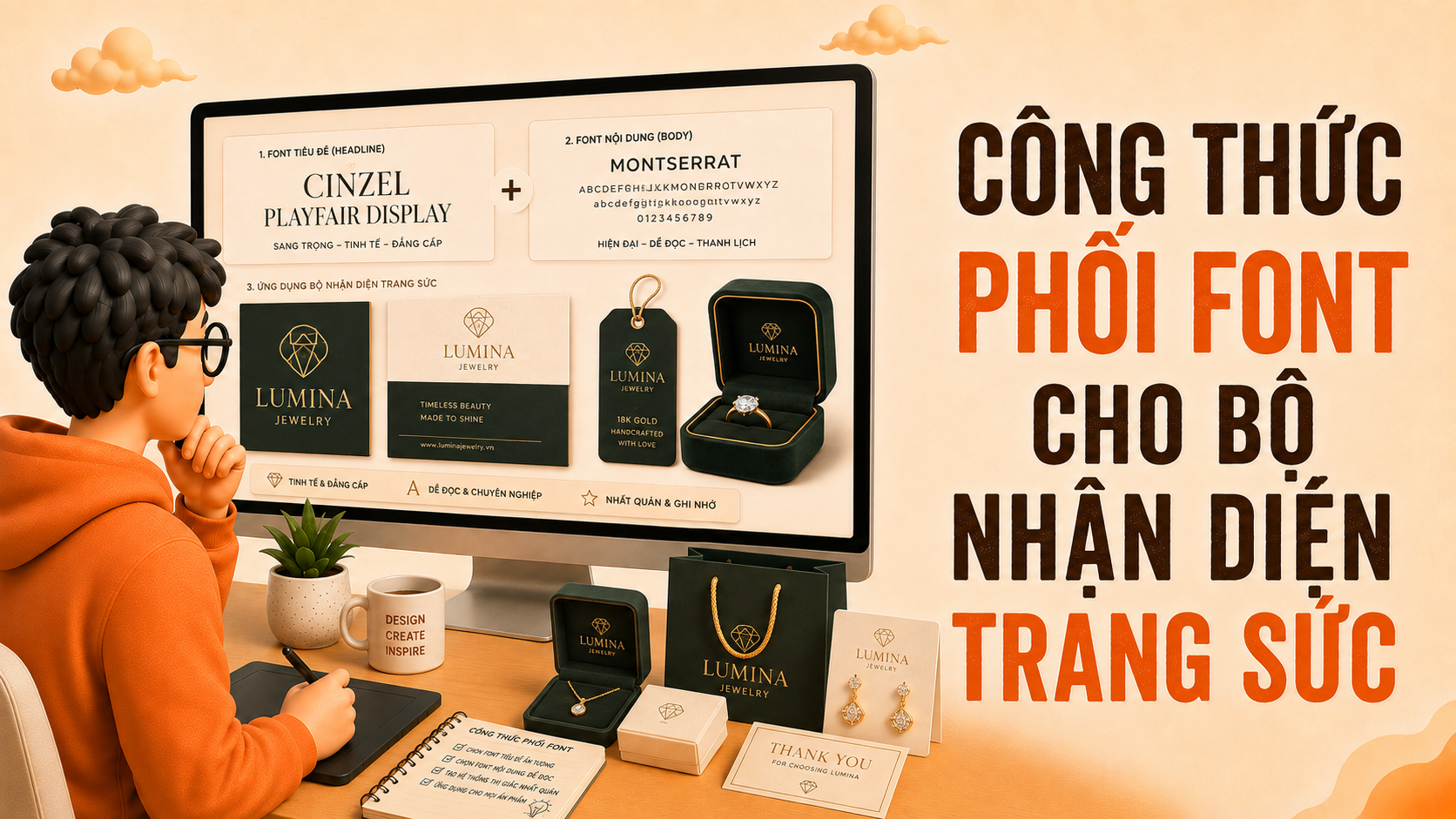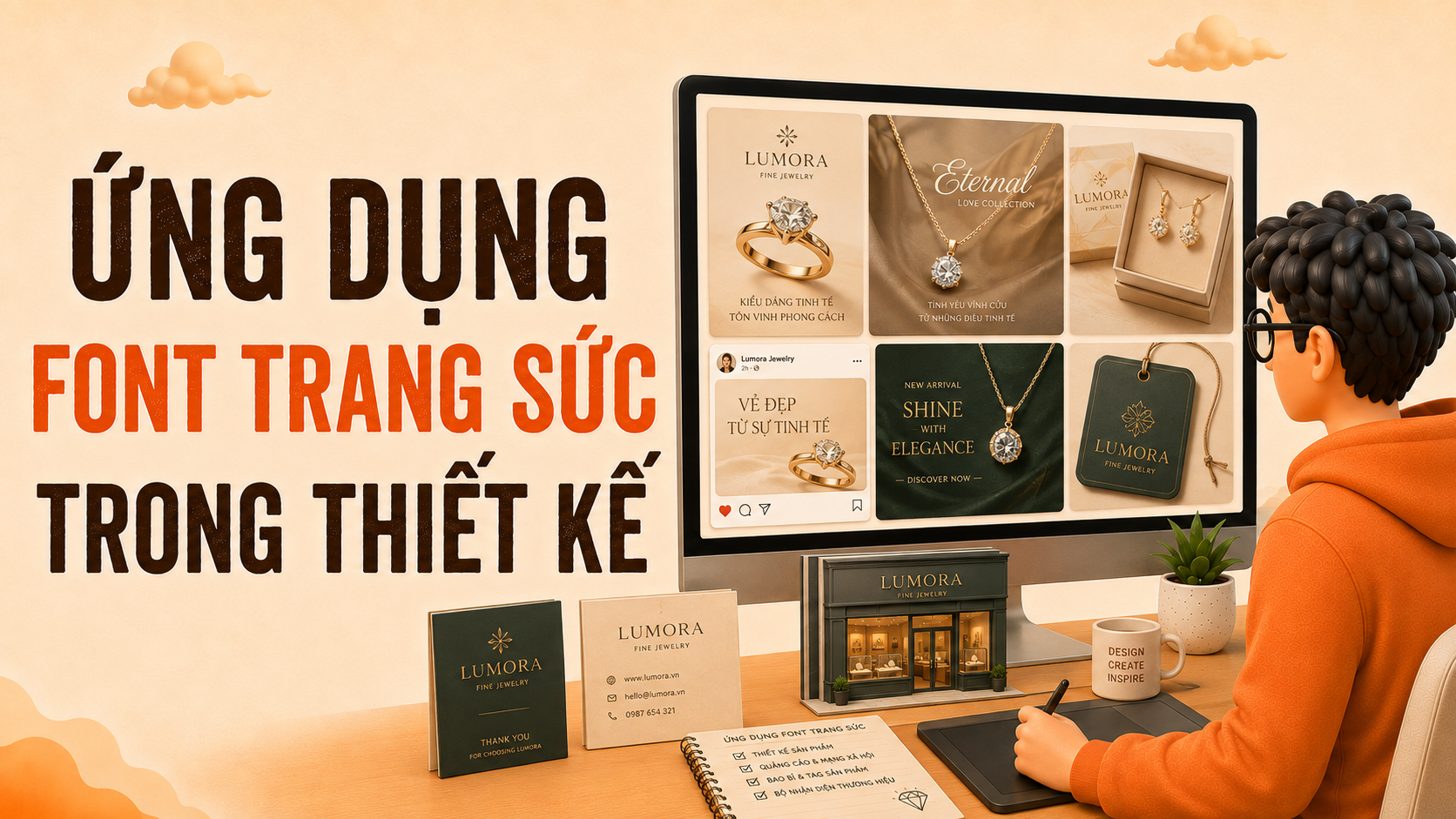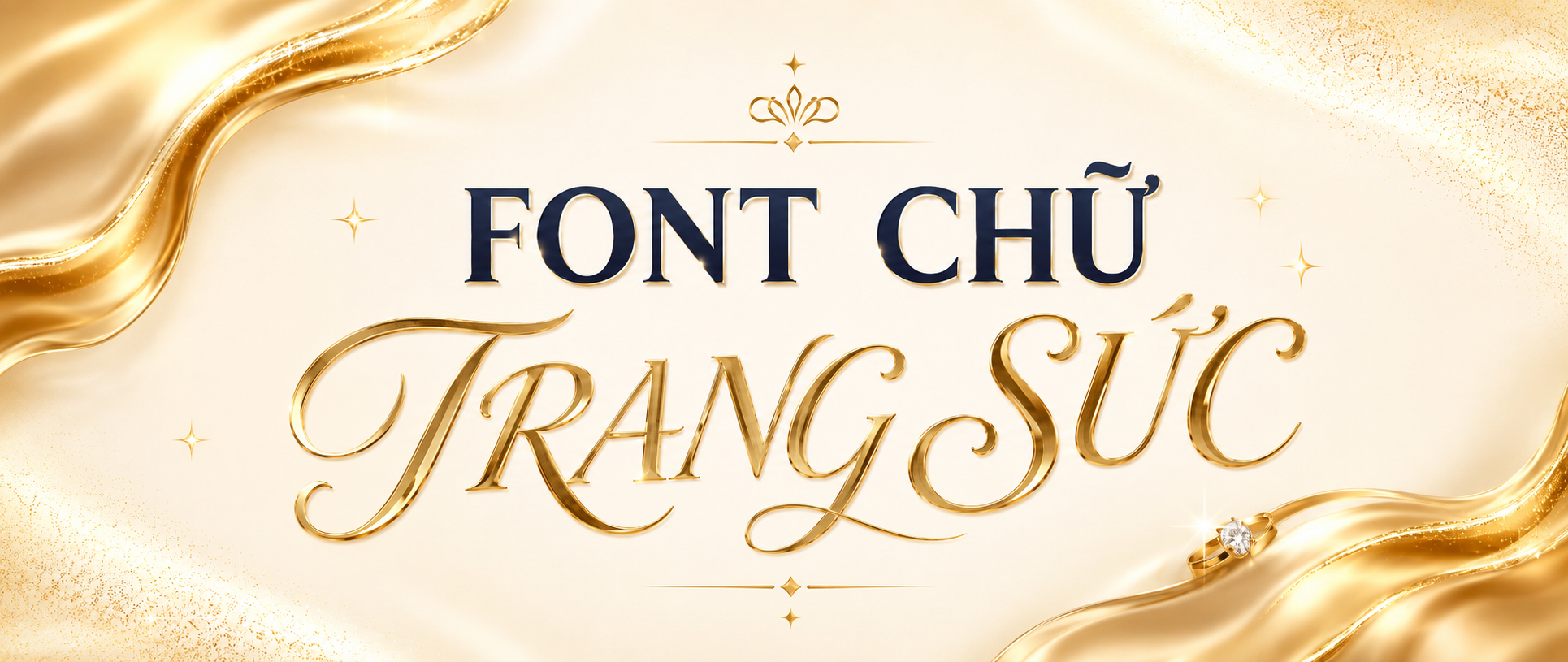
Trang sức là ngành mà chữ rất dễ làm thay đổi cảm giác giá trị. Cùng một chiếc nhẫn, một bộ vòng cổ hoặc một bộ sưu tập bạc, nếu dùng font sai, thiết kế có thể trở nên rẻ, nặng hoặc thiếu tinh tế. Vì vậy, font chữ trang sức cần vừa sang, vừa rõ, vừa giữ được cảm giác tin cậy khi xuất hiện trên logo, hộp đựng, tem nhãn, lookbook, banner sale và social.
Bài viết này gợi ý các font Việt hóa phù hợp trên Font S99 cho nhiều kiểu thương hiệu trang sức: tiệm vàng truyền thống, jewelry cao cấp, bạc tối giản, nhẫn cưới, đá quý, phụ kiện handmade và local brand trẻ. Mỗi font được trình bày thành một dòng riêng với anchor Tải về để bạn dễ chọn và thử trực tiếp trên thiết kế.
Thiết kế trang sức thường có ít chữ nhưng mỗi chữ đều quan trọng. Logo trên hộp nhẫn, tên bộ sưu tập trên lookbook, tagline trên poster, giá ưu đãi trên banner, tên đá quý trên catalogue hay dòng cam kết trên thẻ bảo hành đều góp phần tạo cảm giác cao cấp.
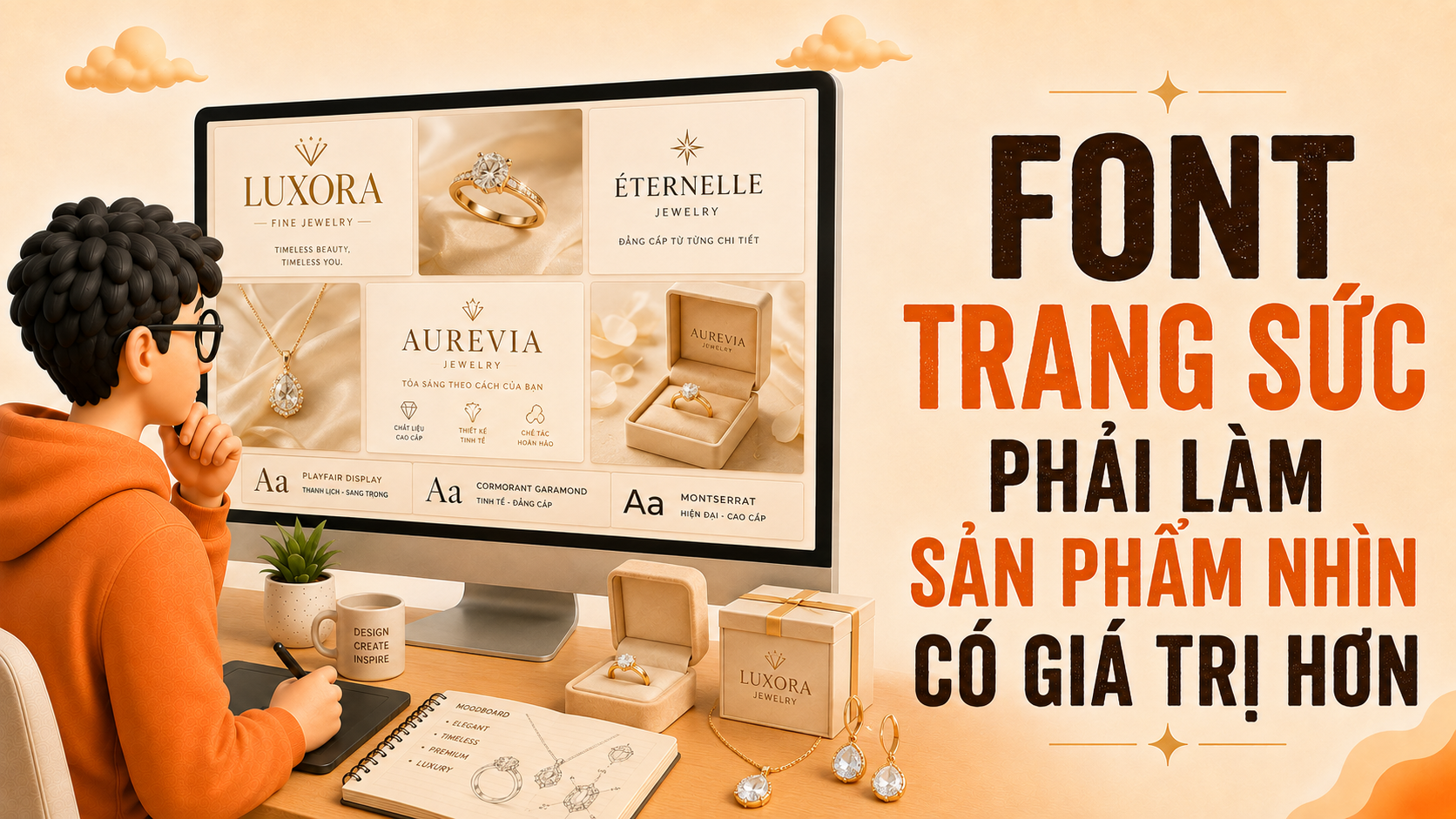
Một font tốt cho trang sức không nhất thiết phải quá cầu kỳ. Nó cần có tỷ lệ đẹp, nét chữ tinh, khoảng cách chữ thoáng và dấu tiếng Việt cân. Với ngành này, sự tiết chế thường sang hơn hiệu ứng. Chỉ cần một font serif thanh lịch hoặc một sans-serif gọn, đặt đúng khoảng trắng, thiết kế đã có thể đắt giá hơn nhiều.
Điểm cần tránh là dùng font quá dày, quá vui hoặc quá nhiều hiệu ứng kim tuyến. Trang sức vốn đã có độ lấp lánh từ ảnh sản phẩm. Font nên nâng sản phẩm lên, không tranh spotlight với sản phẩm.
Logo trang sức nên có cá tính rõ nhưng không khó đọc. Với thương hiệu vàng, đá quý, nhẫn cưới hoặc jewelry cao cấp, serif và luxury sans-serif là lựa chọn an toàn. Với bạc tối giản hoặc local brand trẻ, sans-serif mảnh, sạch và hiện đại sẽ hợp hơn.
Hộp trang sức thường có diện tích nhỏ. Font cần đọc rõ ở kích thước nhỏ, không bị mất nét khi ép kim, in bạc, in vàng hoặc in trên nền tối. Hãy thử logo ở nhiều kích thước trước khi chốt.
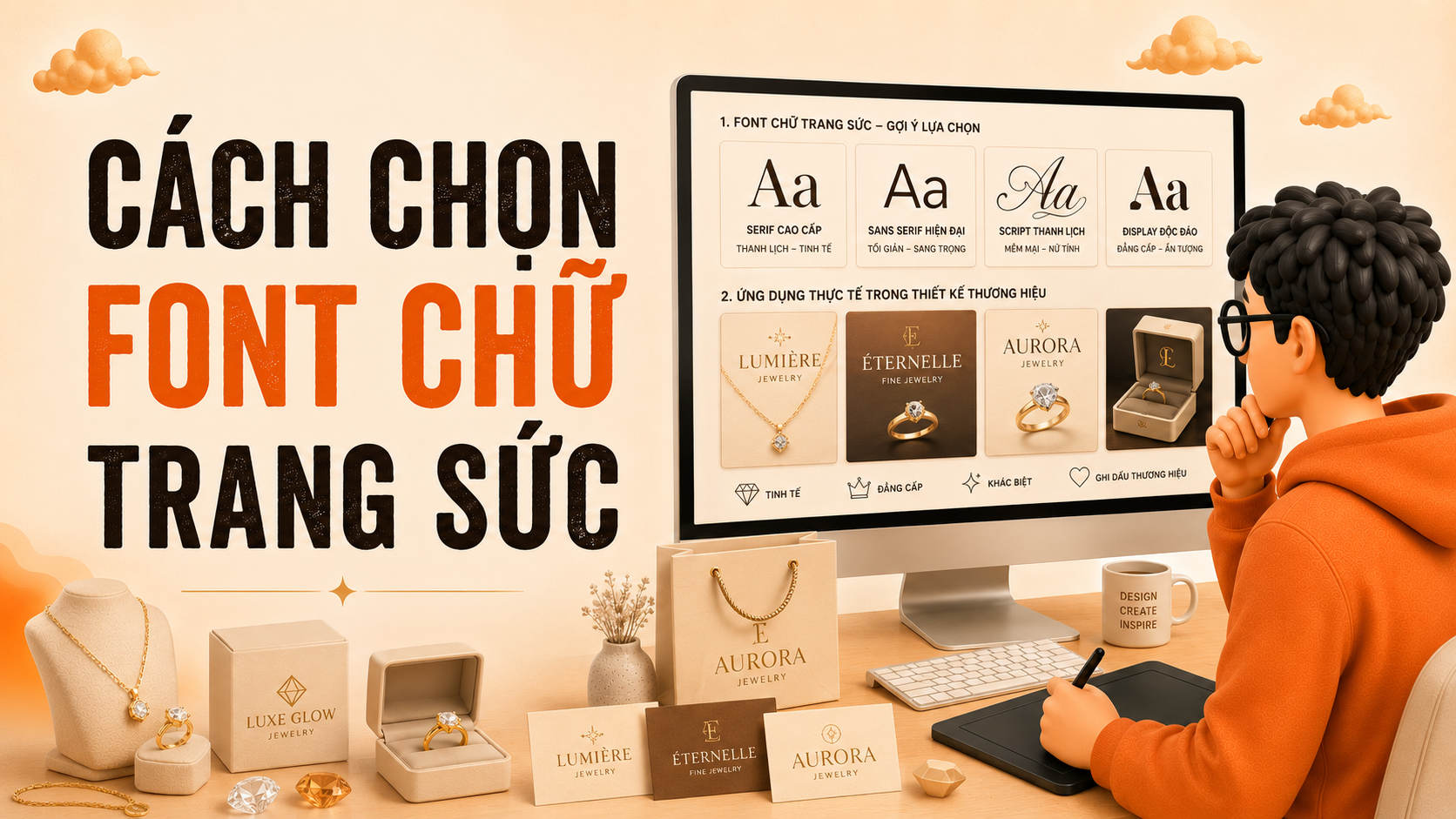
Lookbook cần font tạo nhịp sang trọng nhưng vẫn đọc tốt ở mô tả sản phẩm. Tên bộ sưu tập có thể dùng serif hoặc signature, còn thông tin chất liệu, mã sản phẩm, giá và size nên dùng sans-serif rõ.
Banner trang sức cần nổi bật nhưng không nên quá ồn. Headline như Bộ sưu tập mới, Ưu đãi nhẫn cưới, Trang sức bạc 925, Quà tặng nàng có thể dùng font sang hoặc mạnh hơn; giá, CTA và điều kiện áp dụng vẫn cần font dễ đọc.
Serif là nhóm font rất hợp với trang sức cao cấp. Nét chữ có chân tạo cảm giác cổ điển, tinh tế và đáng tin, đặc biệt khi đi cùng ảnh sản phẩm có ánh kim, nền tối, nền kem, ánh sáng studio hoặc bố cục tối giản.
Nhóm này phù hợp với logo jewelry, tiệm vàng cao cấp, thương hiệu đá quý, nhẫn cưới, bộ sưu tập giới hạn, lookbook và poster thương hiệu. Khi dùng serif, hãy tăng khoảng trắng, dùng ít chữ và tránh đổ bóng quá mạnh. Nét serif đẹp nhất khi nó được thở.
Với tiếng Việt, hãy kiểm tra các cụm có dấu như Trang sức cưới, Vàng 18K, Nhẫn đính hôn, Đá quý thiên nhiên, Bộ sưu tập ánh trăng. Nếu dấu cân và không chạm nét chữ, font có thể dùng an toàn cho logo hoặc headline.
Không phải thương hiệu trang sức nào cũng cần serif. Nhiều thương hiệu bạc, phụ kiện thời trang, trang sức tối giản hoặc local brand trẻ lại hợp với sans-serif sang, gọn và có khoảng cách chữ đẹp. Nhóm này giúp thương hiệu nhìn hiện đại hơn, đặc biệt trên website, Instagram, TikTok Shop và packaging nhỏ.
Luxury sans-serif hợp với logo đơn giản, tên bộ sưu tập, bảng giá, social post, card cảm ơn, giấy chứng nhận và landing page bán hàng. Nếu làm thương hiệu bạc hoặc trang sức minimal, hãy dùng font này với bảng màu trắng, đen, xám, bạc, be hoặc xanh navy.
Một mẹo nhỏ là không nên dùng quá nhiều weight. Trang sức cần cảm giác tinh. Chỉ cần regular, medium và một kiểu tiêu đề là đủ để tạo hệ thống nhận diện sạch.
Signature và script font tạo cảm giác cá nhân, mềm mại và giàu cảm xúc. Đây là nhóm hợp với nhẫn cưới, trang sức cô dâu, quà tặng kỷ niệm, phụ kiện handmade, bộ sưu tập nữ tính hoặc các campaign mang tinh thần lãng mạn.
Nhóm font này nên dùng có kiểm soát. Nó rất đẹp cho tên bộ sưu tập, chữ ký thương hiệu, quote ngắn, thiệp cảm ơn hoặc poster nhẫn cưới. Nhưng nếu dùng cho bảng giá, thông tin chất liệu, size nhẫn hoặc điều kiện bảo hành, người đọc sẽ khó tiếp nhận.
Công thức an toàn là script cho điểm nhấn và sans-serif sạch cho thông tin. Ví dụ, tên bộ sưu tập Nàng thơ có thể dùng script, còn dòng bạc 925, bảo hành, freeship và CTA nên dùng TH Manisans, TH Artega hoặc TH Legacy Sans.
Font chữ trang sức tốt phải làm sản phẩm nhìn có giá trị hơn mà không giành mất sự chú ý của sản phẩm. Hãy chọn serif hoặc luxury font cho cảm giác cao cấp, sans-serif hiện đại cho trang sức bạc và social bán hàng, signature font cho nhẫn cưới hoặc bộ sưu tập nữ tính, rồi luôn kiểm tra dấu tiếng Việt trước khi dùng thật.